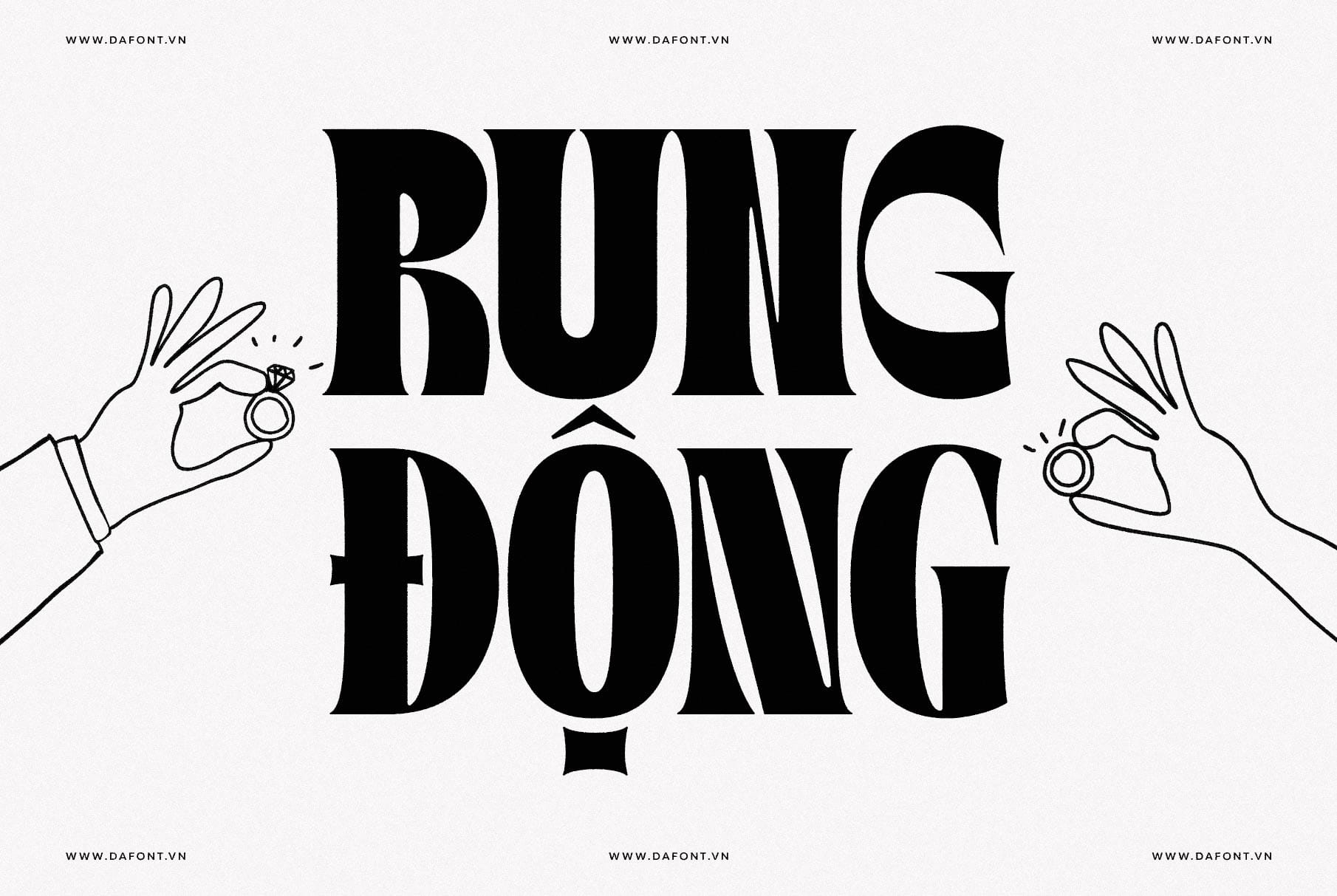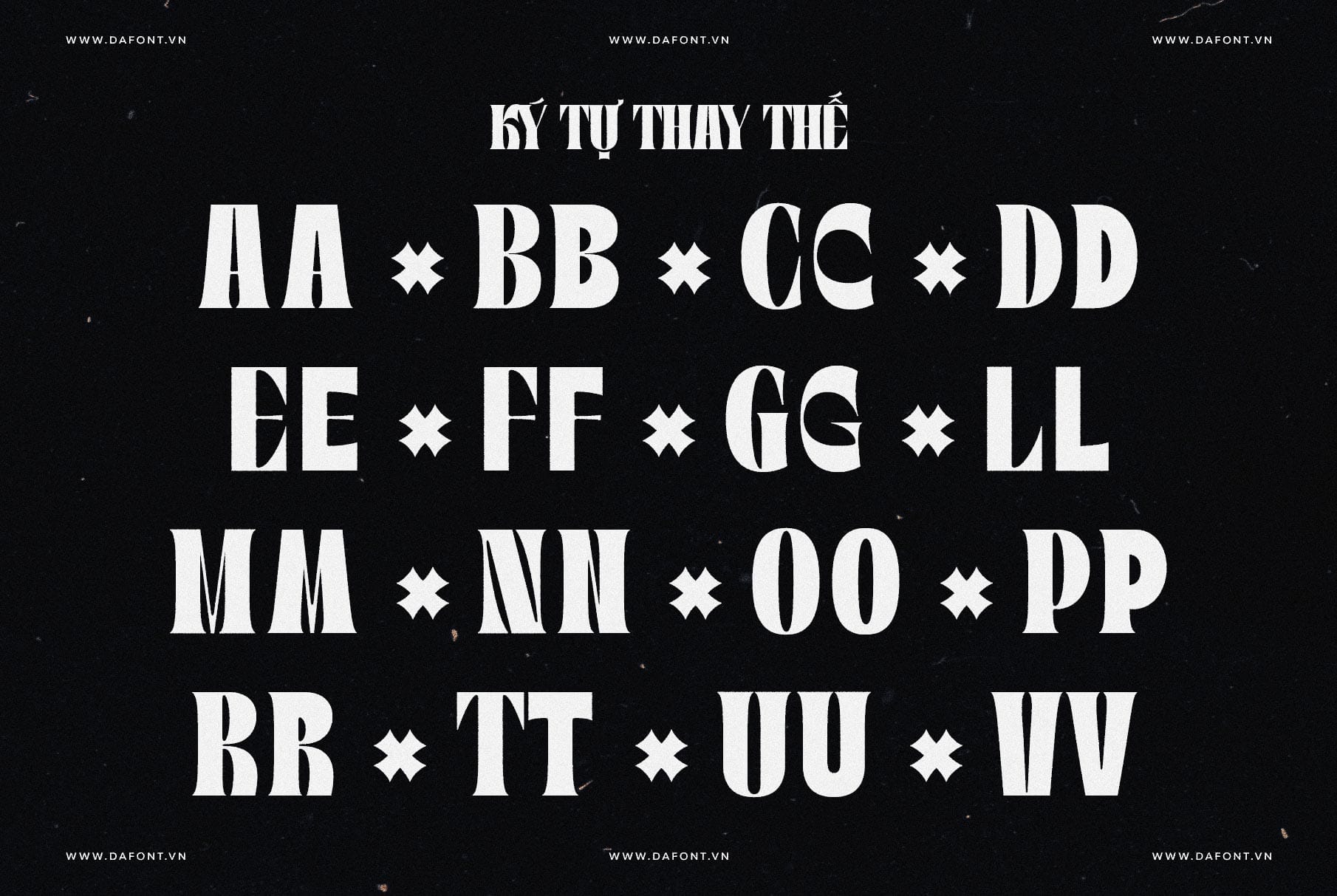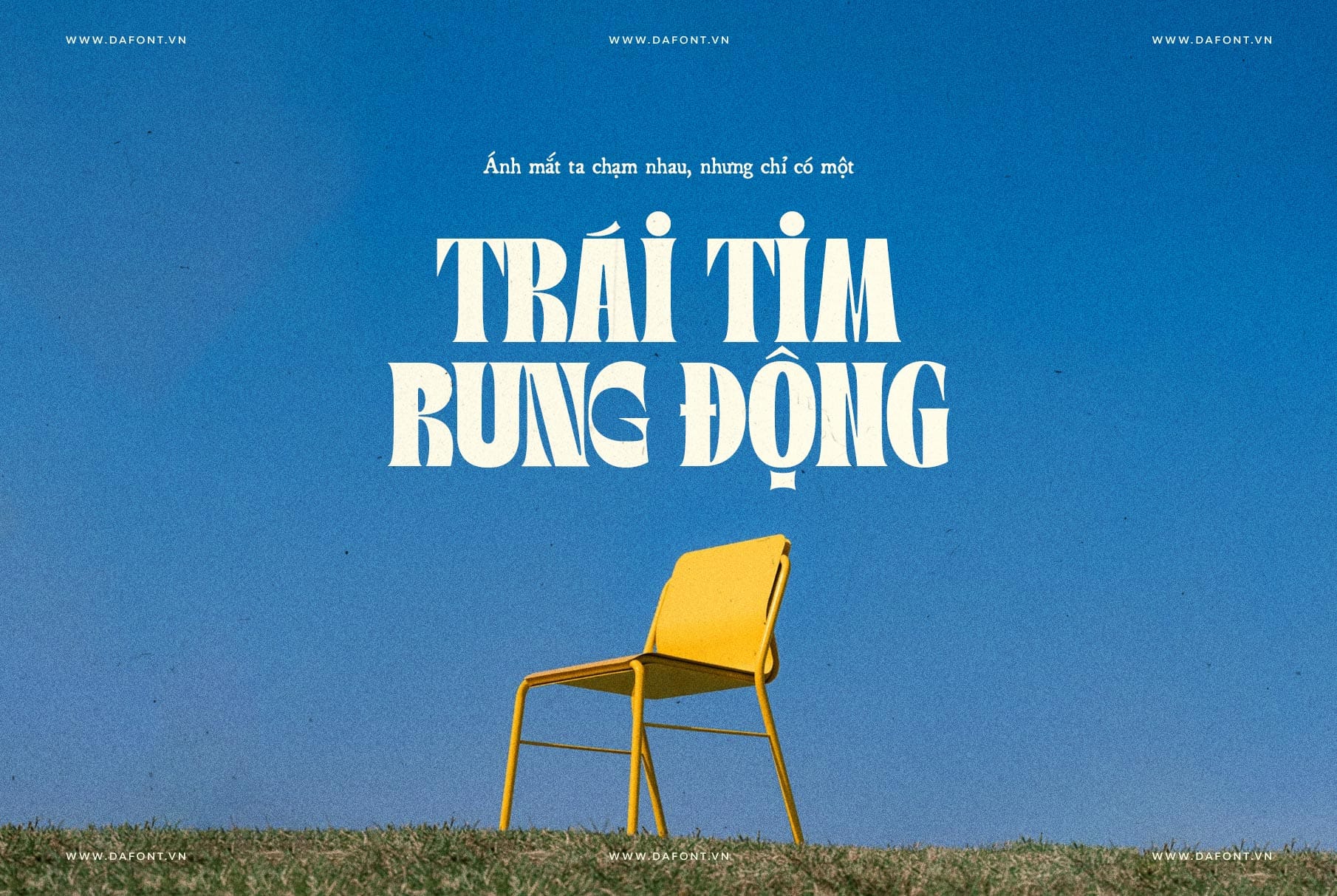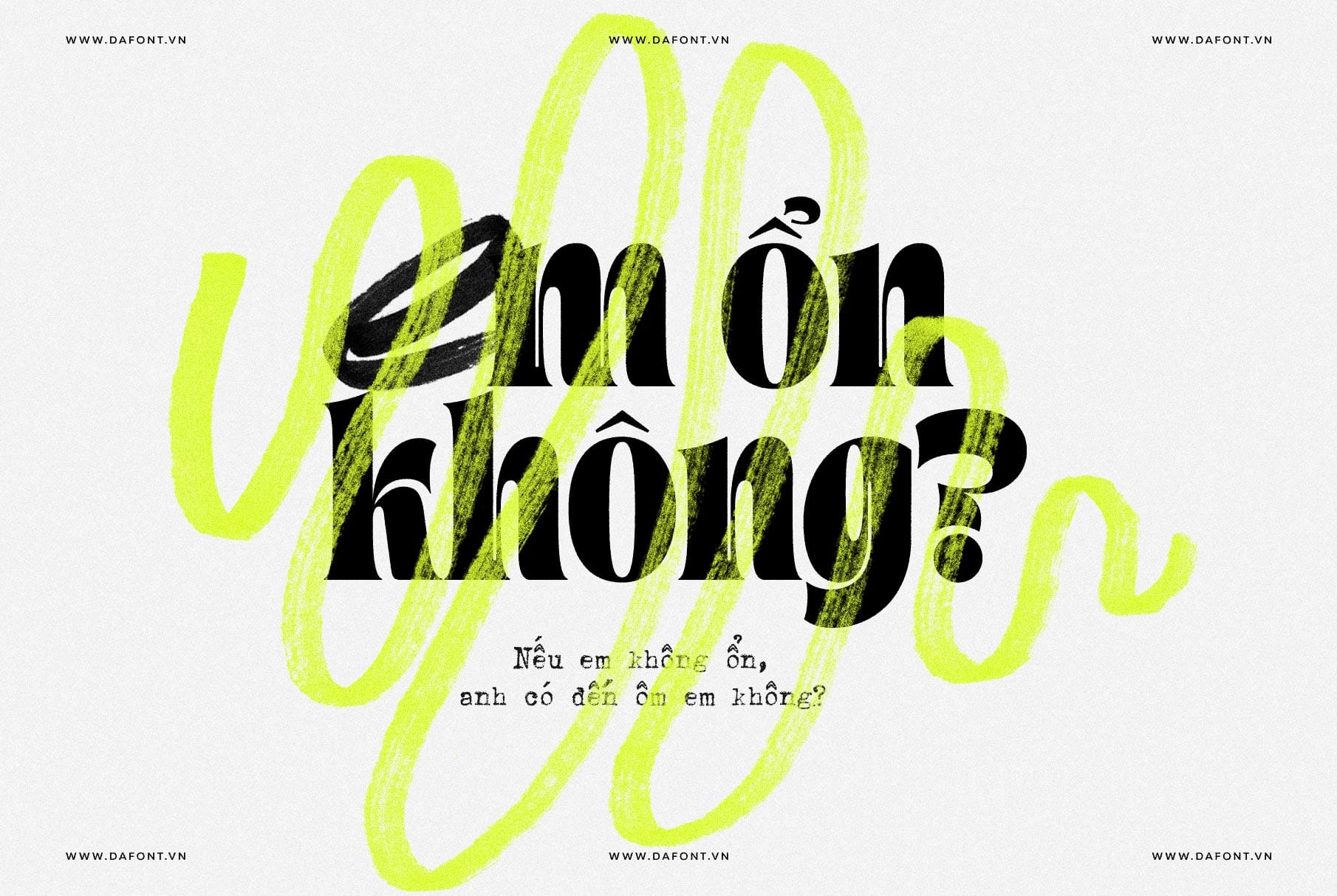
DFVN TAN – KIOSK
Font serif đậm nét retro hoàn hảo cho tiêu đề, poster và branding!
DFVN TAN – KIOSK là một font chữ serif đậm nét retro, kết hợp hoàn hảo giữa sự quyến rũ cổ điển và nét hiện đại. Với các nét chữ mạnh mẽ, phong cách hoài cổ nhưng vẫn tươi mới, đây là lựa chọn lý tưởng cho tiêu đề, poster và các dự án xây dựng thương hiệu. Nếu bạn đang tìm kiếm một retro font để tạo điểm nhấn cho thiết kế của mình, DFVN TAN – KIOSK chắc chắn sẽ không làm bạn thất vọng.
Đặc điểm ấn tượng của DFVN TAN – KIOSK
TAN – KIOSK là sự hòa quyện độc đáo giữa phong cách retro font và sự tinh tế hiện đại. Dưới đây là những đặc điểm thiết kế làm nên sức hút của nó:
• Nét serif đậm: Các nét chữ mạnh mẽ, tự tin giúp TAN – KIOSK dễ dàng thu hút ánh nhìn ngay từ đầu.
• Vẻ đẹp hoài cổ: Mang đậm phong cách vintage typography, gợi nhắc về những thiết kế kinh điển trong quá khứ.
• Chạm đến hiện đại: Dù mang hơi hướng retro, TAN – KIOSK vẫn giữ được nét tươi mới, phù hợp với xu hướng thiết kế đương đại.
Nhờ những đặc điểm này, DFVN TAN – KIOSK không chỉ độc đáo mà còn nổi bật giữa hàng ngàn font chữ serif khác, trở thành một kiểu font ấn tượng cho nhiều dự án thiết kế.
Lý tưởng cho nhiều dự án thiết kế
Với tính linh hoạt và sức hút riêng, TAN – KIOSK là lựa chọn hoàn hảo cho nhiều loại dự án thiết kế. Dưới đây là một số cách bạn có thể ứng dụng phông chữ này:
• Tiêu đề nổi bật: Nhờ nét chữ đậm và phong cách retro, TAN – KIOSK rất phù hợp cho các tiêu đề lớn trên website, tạp chí hay banner.
• Áp phích và Poster: Bạn muốn tạo một poster mang cảm giác vintage typography nhưng vẫn hiện đại? TAN – KIOSK sẽ giúp bạn đạt được điều đó.
• Xây dựng thương hiệu: Font chữ này mang lại cá tính mạnh mẽ, lý tưởng cho các thương hiệu muốn tạo ấn tượng với chút hoài cổ.
Dù bạn đang thiết kế cho ngành thời trang, ẩm thực hay nghệ thuật, DFVN TAN – KIOSK đều có thể nâng tầm dự án của bạn với phong cách bold serif đặc trưng.
Mẹo sử dụng DFVN TAN – KIOSK hiệu quả
Để khai thác tối đa tiềm năng của TAN KIOSK, bạn hãy thử áp dụng những mẹo sau:
• Kết hợp với thiết kế tối giản: Sử dụng phông chữ này trong các bố cục đơn giản để nó trở thành điểm nhấn chính.
• Tăng kích thước: TAN KIOSK phát huy tối đa sức mạnh ở các kích thước lớn, đặc biệt là trong tiêu đề hoặc logo.
• Chọn màu sắc phù hợp: Kết hợp với màu sắc tương phản để làm nổi bật nét chữ, hoặc chọn tông màu vintage để tăng cảm giác hoài cổ.
Những mẹo này có thể sẽ giúp bạn sử dụng DFVN TAN – KIOSK một cách hiệu quả, tạo nên những thiết kế vừa đẹp mắt vừa ấn tượng.